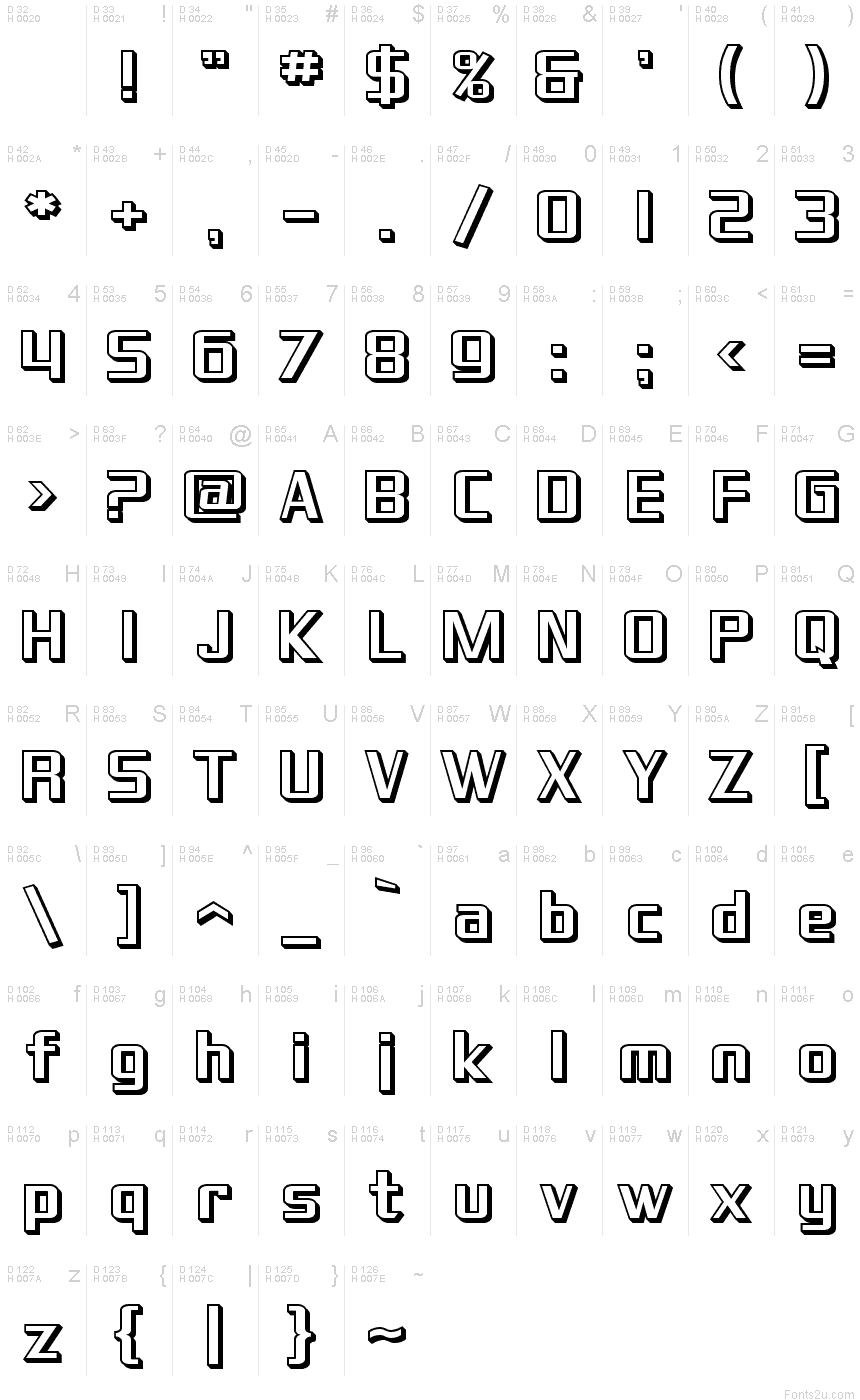
SF Theramin Gothic Shaded di ShyFonts Type Foundry è un font display moderno e gratuito, caratterizzato da un elegante tocco techno di fine XX secolo. Le lettere sono costruite con forme ampie e squadrate e spazi interni aperti, mentre l'ombra sfalsata conferisce all'intero design una profondità nitida e scalettata, a differenza del classico effetto 3D morbido.
Si adatta naturalmente ai titoli di poster, loghi di giochi, packaging musicale, copertine sci-fi e branding deciso, dove un font gratuito deve creare un'atmosfera immediata senza effetti aggiuntivi. Poiché l'ombreggiatura è parte integrante del disegno, funziona particolarmente bene per titoli brevi, schermate di presentazione e monogrammi che necessitano di un impatto tridimensionale integrato.